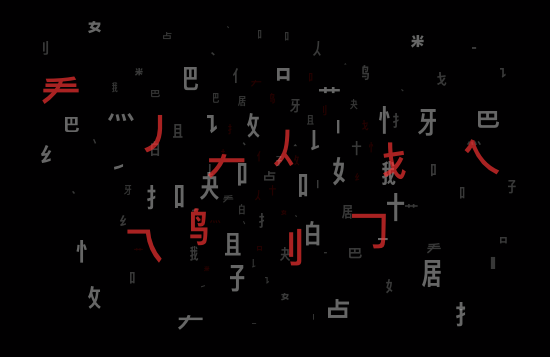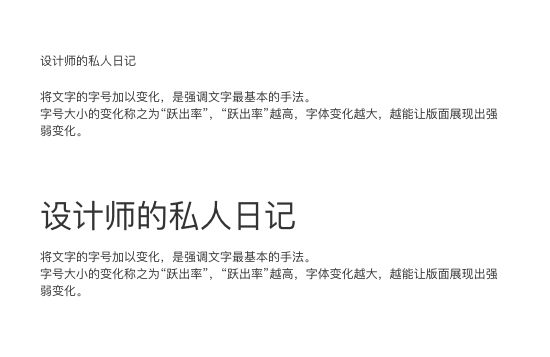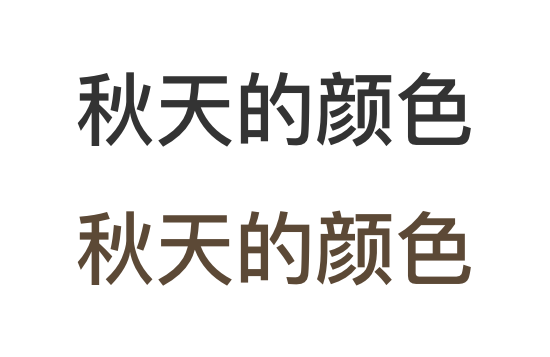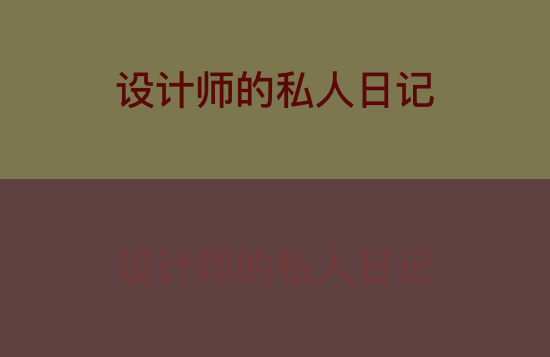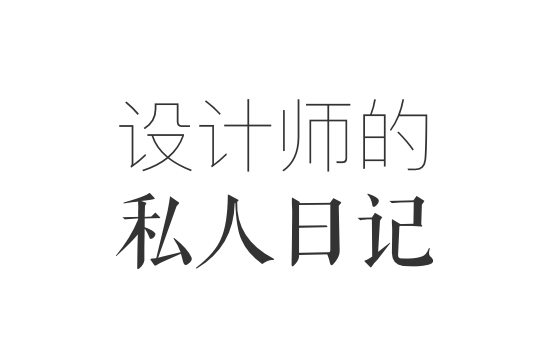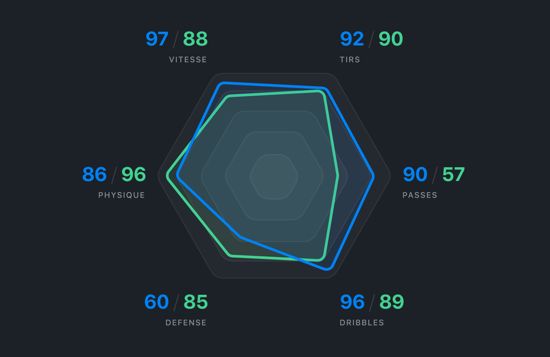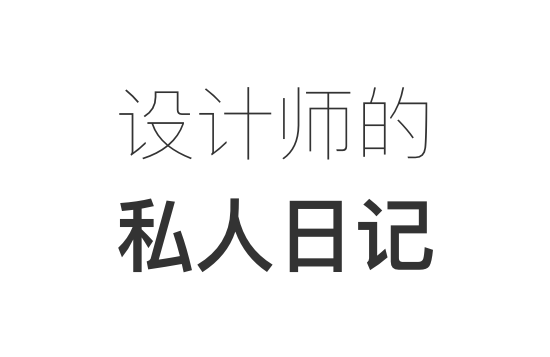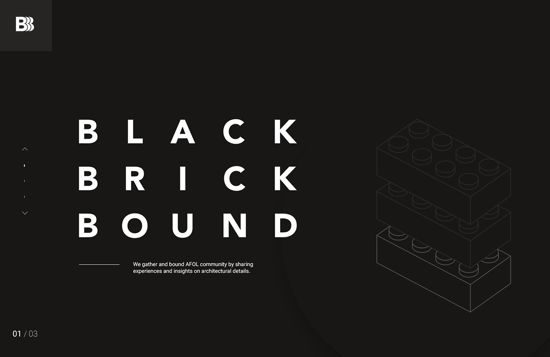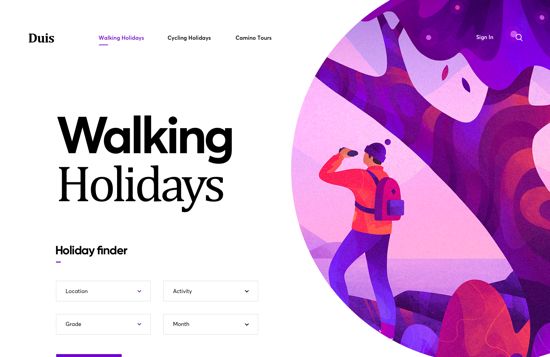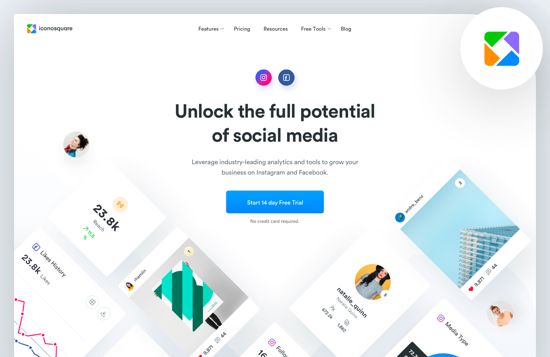
介绍几种字体设计最具代表性的表现方法
//前言//
人们为了传递某些信息,而去书写文字。设计就是为了传达某些信息,让观者读取文字的时候,在心中能够留下强烈的印象。
本着这个目标,我们考虑将文本的“易读性”向前更进一步,使得文本更具有“表现力”。
在下面的分享中,介绍几种最具代表性的表现方法;在阅读时,思考画面适合用哪几种表现手法,在何时能够发挥最佳效果。如此一来,学习效果才会更好。
//字号对比//
将文字的字号加以变化,是强调文字最基本的手法。
字号大小的变化称之为“跃出率”,“跃出率”越高,字体变化越大,越能让版面展现出强弱变化。
文字字号大小的变化,也会影响版面的“平衡”。文字越大,其所在之处的“重量”也会越大;同样,小字号的文字,数量够多,“重量”也会越大。
所以,我们在版面配置文字的时候,会考虑文字之间互相造成的重量抗衡关系,通过字号加大,或者字量增加来调整版面的平衡。
文字大小变化还有一个目的就是整理信息。尤其是在长篇文字时,如果字号全部相同,那么读者可能会觉得需要把通篇都读完才能掌握内容;而局部使用大字号的文字,读者通过浏览突出内容,就更容易掌握整体。
//重量对比//
把字的重量加以变化,版面也会产生强弱的差别。
所谓的“重量”是指文字的线条粗细。大部分的标准字体,都会准备好几种的重量形态。
相同字号的字体,借助字的重量的变化来表现强弱。最引人注目的标题或者标语处,使用粗线条的字,周围配套内容使用细线条,使得观者的视觉焦点集中在重量较大的文字上。
此外,字体的重量也可以决定文字内容的重要性。线条越粗感觉越沉重,反之,线条越细感觉越轻巧。换言之,字体的重量也就是版面中的“存在感”。
字号小而线条粗的文字,与字号大而线条细的文字,展现出来的存在感差不多。虽然存在感差不多,但是字体的重量有所差异,传达出来的印象也随之不同。
在思考如何设计文字内容时,要结合文字的字号和重量;在版面上表现强调和节奏时,要注意对比的基本原则-不要畏手畏脚。
//字体对比//
在字体上增添变化,可以让观者感受到设计师的“在意”。
如果文字内容全局使用样式相同的字体,会让人觉得设计师的不用心;而全局使用不同样式的字体,会让人觉得“异样感”,文章就会难以阅读;但若只是作为设计的点缀,运用在某一部分,就可以产生强调的效果。
为字体赋予变化时,如果只是稍许的差异,无法达到预期的对比效果;重量轻的字体也难以区分彼此的差异。因此,想要营造字体的对比效果,就使用重量重的字体来彼此搭配组合,或是加重某一方的重量来达到对比效果。
相对于重量或者字号对比,字体对比更能够将观者的注意力集中在文章的“内容”上。想要进一步强调时,添加颜色的变化也是一种方法。
//色彩对比//
若想要强调某一部分时,改变文字颜色是极为有效的办法。
在设计中,色彩是极为重要的要素,在传达无法言喻的感觉时,灵活运用配色是最有效的方法。
颜色使用在文字上时,为了提高文字的可读性,必须使背景色与文字的色彩有明度落差。
将色彩当做特点使用时,尽量减少颜色数量,或者统一色彩的色调,营造整体和谐的感觉。
//节奏//
在版面上创造出节奏,那个部分就会成为目光的焦点。
想要展现节奏感,就要从“静止”与“动感”两方面着手。
所谓的“静止”就是完全依照规则、正确排列文字等要素的状态,这是表现节奏感的基础。
在“静止”状态下,从要素中选取某一部分,将其放大、加粗,或者是改变颜色,利用这种变化来表现“动感”,进而产生节奏。
虽说想要强调节奏感,但若将所有的要素都加上“动感”,整体就会散发出杂乱但感觉,务必保留基础“静止”部分。
//材质//
在文字上使用“材质”,可以获得戏剧化的效果。
在文字上体现材质感的优点是可以呈现复杂且具体化的感觉,这是单一色彩无法赋予的。
采用有材质感的文字,虽然是文字,同时也具有画面效果。一般的文字,无法融入画面,但是采用材质感的文字,版面会有融合的感觉。
//紧排与宽排//
极端紧缩文字间隔,可以营造出紧张感与密度感;字距之中的空隙,可以展现轻松柔和的空间感。
文字与文字的间隔(字距)或是行与行之间的间隔(行距),关系到文章的可读性与易读性,这是非常重要的设计要点。
将字距或行距缩小,称为“紧排”。一般来说,稍微紧缩字符间距,可以让整行文字更容易阅读,映入眼帘中的只有其为文字组块的部分,并且拥有一种力道强劲的印象与一体感。
将字距或行距拉开,称为“宽排”。借由这种宽松来产生一种可以悠闲阅读文字的效果。
//小结//
文字的使用是为了传达信息,以能够理解文字显示内容为前提来进行排版设计;也可以把文字当做图案来处理。
更进一步,使用一些加工技巧让文字变形或是重叠,创造出新的图案。
不要只是将文字当做一种信息来看待,偶尔重新审视其形状,这样才可以更加理解文字。